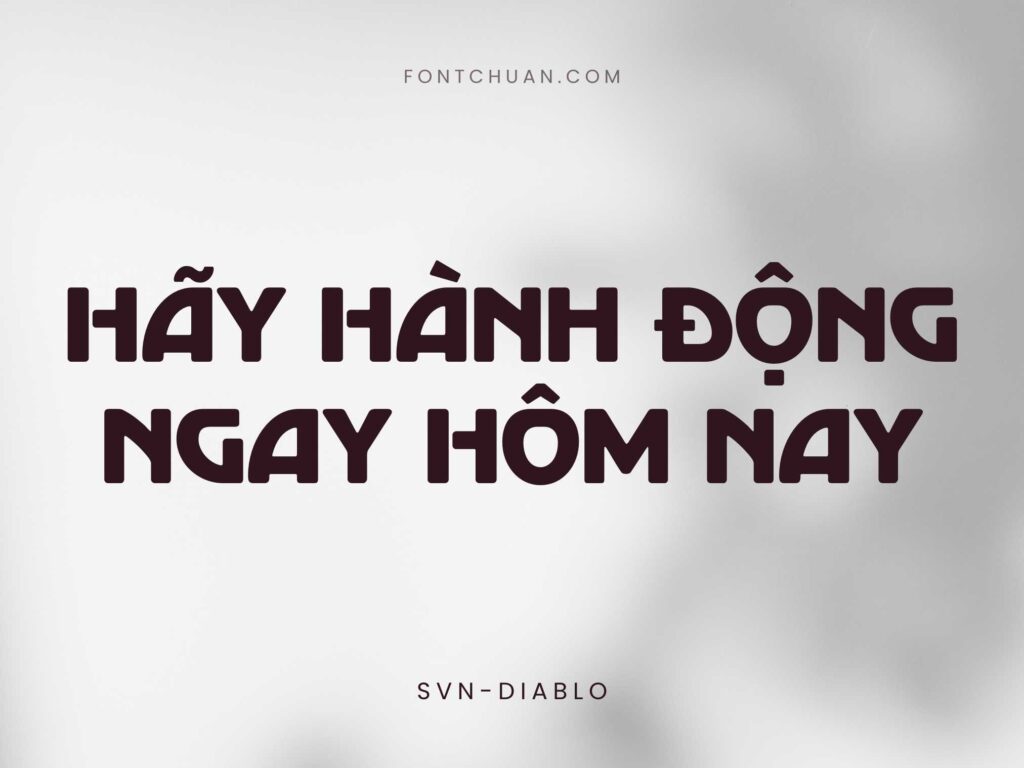
Font SVN Diablo Việt Hóa
Tác giả Font: Jim Parkinson
Diablo là một font chữ mang phong cách Gothic, được thiết kế bởi một nhà thiết kế không rõ tên tuổi. Font này có kiểu chữ đậm, với các đường nét sắc sảo và mạnh mẽ, tạo nên ấn tượng mạnh mẽ trong thiết kế. Với vẻ ngoài huyền bí và ma mị đặc trưng, Diablo còn được xem là một Font chữ Halloween lý tưởng, phù hợp cho các dự án cần không khí rùng rợn hoặc kỳ bí. Font đã được Việt hóa để hỗ trợ tiếng Việt bởi Styleno.1 Fonts, đồng thời hỗ trợ nhiều ngôn ngữ khác, giúp mở rộng phạm vi sử dụng trên toàn cầu. Font này được chia sẻ miễn phí cho mục đích sử dụng cá nhân trên trang Styleno.1 Fonts, đáp ứng nhu cầu của người dùng và ứng dụng thực tế vào các dự án thiết kế.
Đặc điểm thiết kế của Diablo bao gồm các nét chữ Gothic đậm, tạo cảm giác huyền bí và cổ điển. Font này phù hợp cho các ứng dụng như tiêu đề, logo, poster, bìa sách và các dự án sáng tạo khác. Các ngành nghề phù hợp bao gồm quảng cáo, nghệ thuật và thiết kế đồ họa.